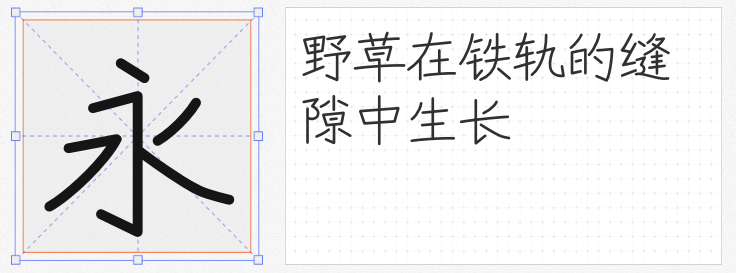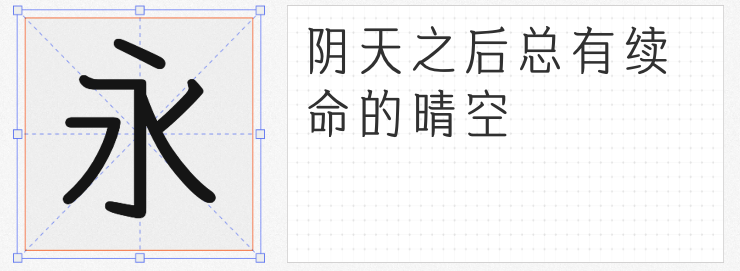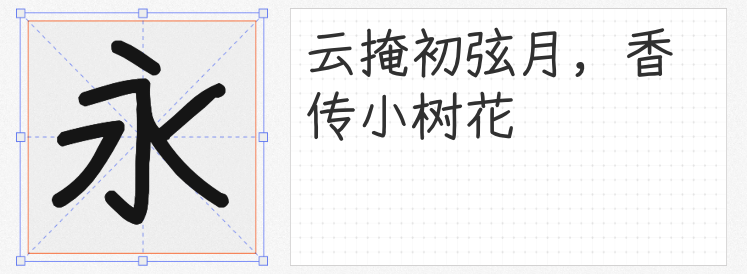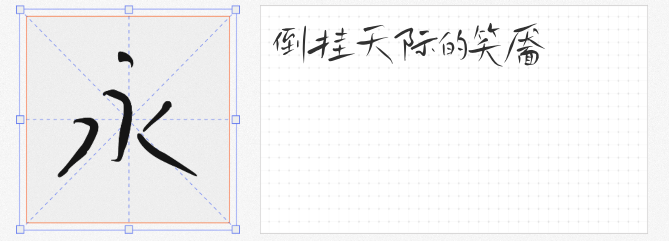
在数字设计领域,手写字体以其独特的温度感与人文气息,成为品牌叙事与视觉表达的重要载体。本文精选四款免费商用、风格迥异的手写字体,从传统宫廷美学到现代随性笔触,为设计师提供多元创作选择。
作为韩国首款多语种正文字体,韩契在民体6.0 CN以1908年《大韩国会开幕原则书》中的宫廷书法为基底,融合现代几何设计哲学。其核心创新在于将韩屋屋顶的波浪曲线与韩服缎带袜的流畅线条抽象化,形成「外柔内刚」的视觉张力——「ㅇ」辅音取自淑明公主笔迹,以稚嫩端方的笔触传递女性宫廷字体的尊严感;「ㄹ」与「ㅎ」辅音经几何化处理后,在保持手写韵味的同时强化现代感。该字体支持11,172个韩文字符、6,763个简体中文及多语种符号,适用于文化类海报、书籍装帧等需要东方美学表达的场景。
由独立设计师落霞孤鹜开发的悠哉字体,通过深度学习技术补全CJK统一表意文字基本区20,992字,实现简体中文、繁体中文、日文假名的全覆盖。其设计亮点在于字面缩小至原Y.OzFont的95%,优化西文字符与中文的视觉平衡;新增Medium字重版本,解决原版笔画过细的缺陷。作为GB2312标准汉字的完整实现者,该字体在电商详情页、UI界面等实用场景中表现出色,尤其适合需要多语言支持的跨国品牌设计。
写意体SC以中性笔书写特性为灵感,通过「Written」的命名强调其返璞归真的设计理念。字体开发者针对简体中文显示不足的问题,重构字形并优化笔画粗细过渡,形成圆润柔和的视觉效果。尽管字符集仍在完善中,但其独特的「未完成感」恰好契合年轻化品牌追求的随性气质,在社交媒体图文、独立音乐专辑封面等领域展现出独特魅力。
这款看似随意的字体实则暗藏设计智慧——通过控制笔画倾斜角度与连笔节奏,在保持手写真实感的同时确保98%以上的辨识度。其应用场景横跨餐饮品牌包装、文创产品标签到儿童读物封面,证明「不完美」设计同样具备商业转化力。